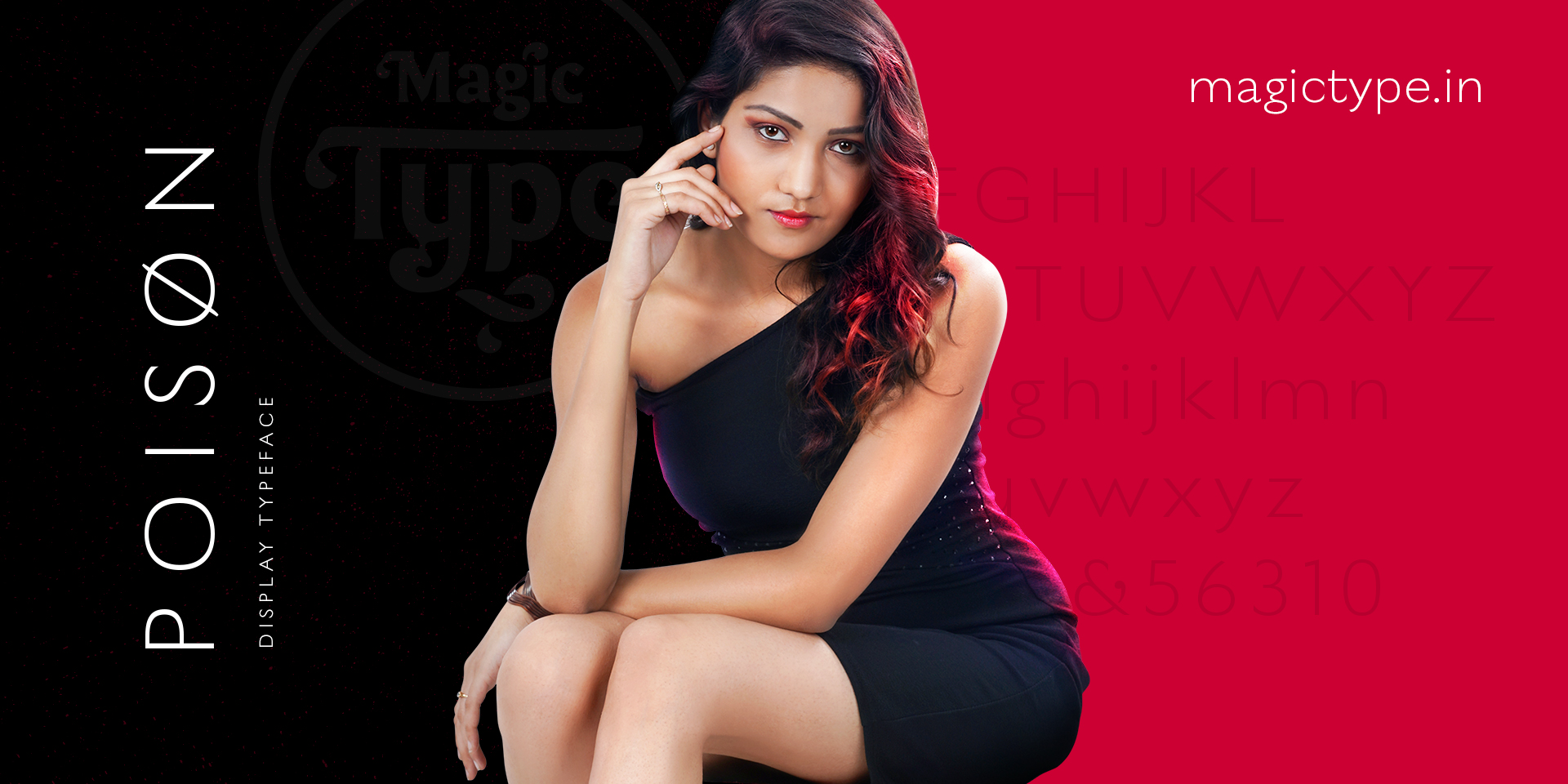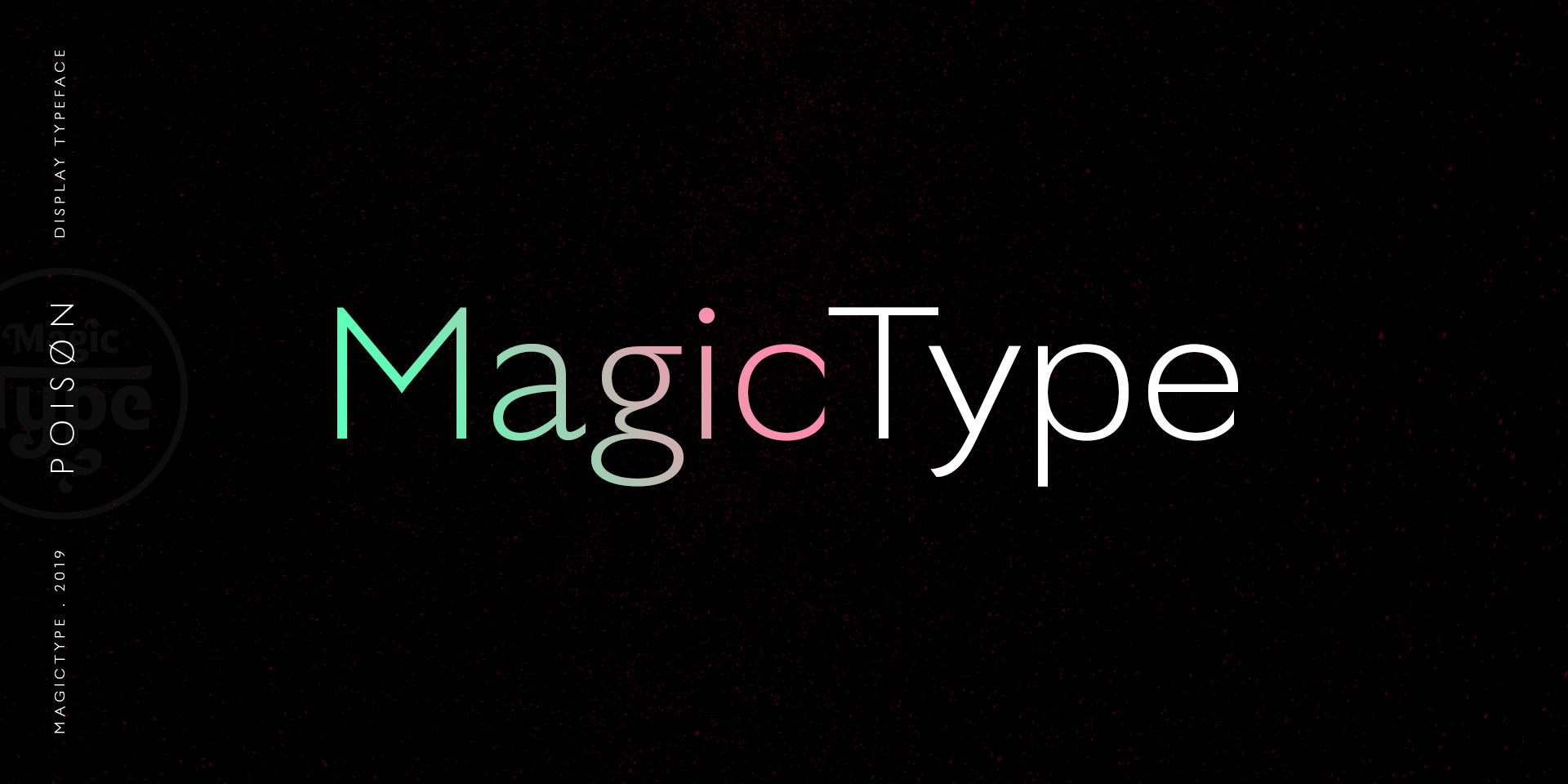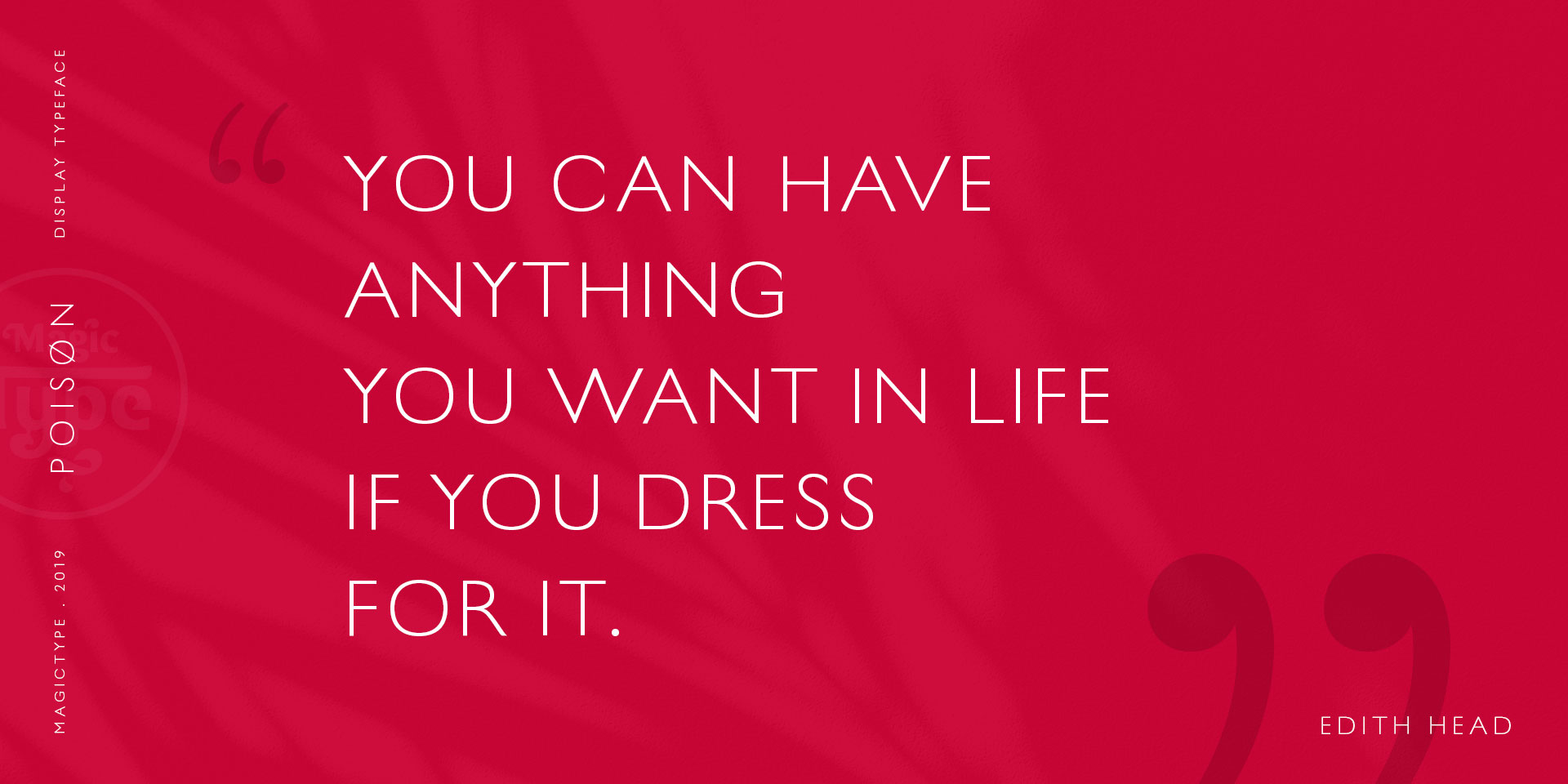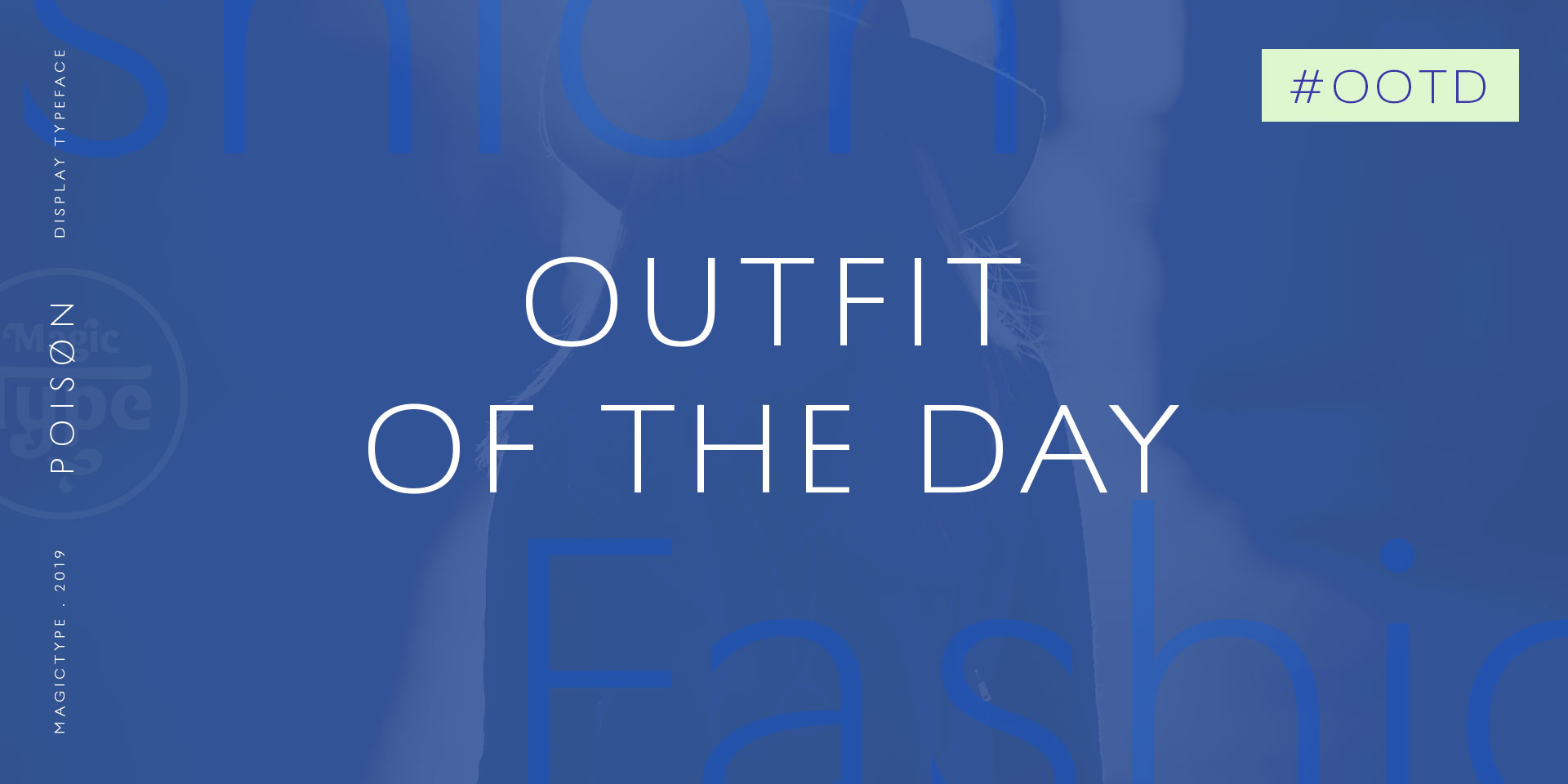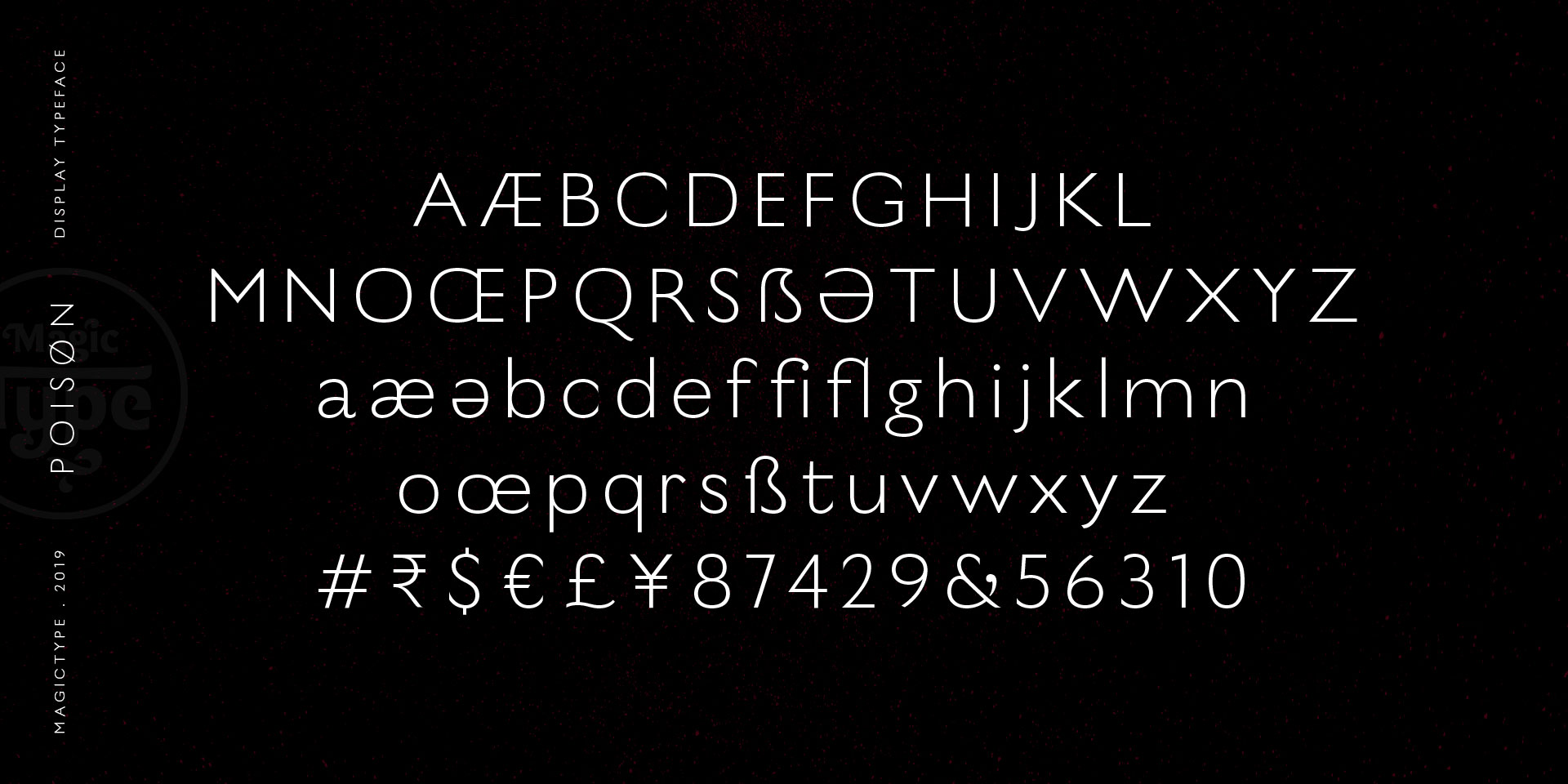
Poison
Poison 是一款以“魅惑与危险美学”为设计灵感打造的现代拉丁展示字体(Display Typeface)。字体通过极简的线条结构、均衡的笔画比例以及独特的几何造型,将优雅、神秘与疏离感融入字母设计之中,形成一种兼具时尚感与实验性的视觉风格。
Poison:融合几何线条与冷感美学的现代英文展示字体
从整体字形来看,Poison 采用较为纤细且均匀的线条构建字母骨架,没有明显的粗细变化,使字体呈现出轻盈、理性的现代气质。字母结构强调几何比例与空间关系,通过精准控制字面宽度、留白以及字母间距,让整体排版拥有较强的秩序感。相比传统纤细无衬线字体,Poison 并未追求单纯的简洁,而是在规则结构中加入细微的造型变化,使字体更具辨识度。
Poison:融合几何线条与冷感美学的现代英文展示字体
在细节设计方面,Poison 最大的特点在于圆润曲线与几何结构之间的结合。部分字母采用柔和的弧线处理,例如圆形字腔、流畅转角以及开放式结构,使字体避免了过度机械化的冰冷感。同时,简洁锐利的线条又赋予字体一定的距离感与现代感,形成“柔美外观与冷静内核”并存的视觉效果。这种矛盾性的设计语言,也呼应了字体名称 Poison 所代表的“危险吸引力”概念。
Poison:融合几何线条与冷感美学的现代英文展示字体
从排版表现来看,Poison 更适合作为展示用途字体使用。纤细的字形结构能够在大字号环境下展现优雅的轮廓,非常适合用于品牌标识、时尚海报、杂志标题、美妆包装、艺术展览以及高端视觉设计等场景。由于字体本身具有较强的风格属性,在短文本和标题排版中能够形成鲜明的视觉焦点,而在长篇正文中则不建议作为主要阅读字体使用。
Poison:融合几何线条与冷感美学的现代英文展示字体
从字体气质来看,Poison 结合了现代极简主义、未来感设计以及轻奢视觉语言。它没有传统装饰字体的复杂元素,而是通过比例、线条和负空间创造独特的视觉张力。黑色背景下,纤细字形呈现出清晰冷静的轮廓;搭配明亮或高饱和色彩时,则能够进一步强化字体的时尚感与艺术表现力。
Poison:融合几何线条与冷感美学的现代英文展示字体
Poison 是一款通过极简结构表达复杂情绪的现代展示字体。它将几何理性与柔和曲线结合,在简洁的字形中融入神秘、优雅与危险感,形成独特的视觉个性。对于需要突出品牌气质、艺术氛围或现代时尚感的设计项目而言,Poison 提供了一种具有辨识度的排版选择。